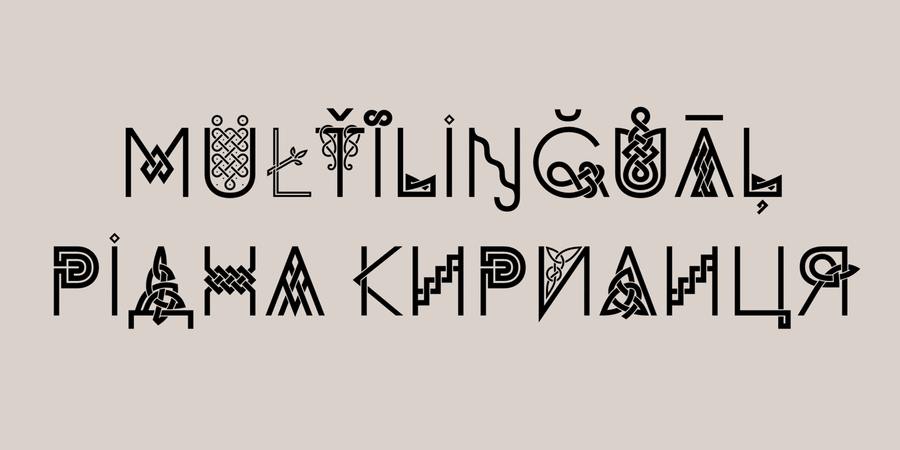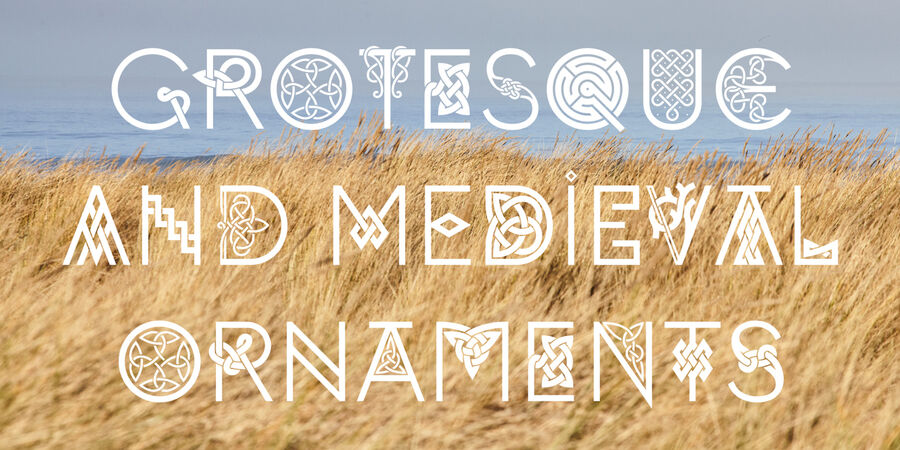
Шрифт зроблений під враженням від середньовічних рукописних книг. Форми знаків частково запозичені у прототипів, але в більшій мірі відображають фантазії автора на кельтську тему. Особливістю шрифта є поєднання середньовічної естетики з формами сучасного геометричного гротеску. Шрифт містить велику кількість альтернатив і дискретних лігатур, що дозволяє зробити неповторні комбінації літер. Шрифт розробив Лук'ян Турецький у 2024 році.